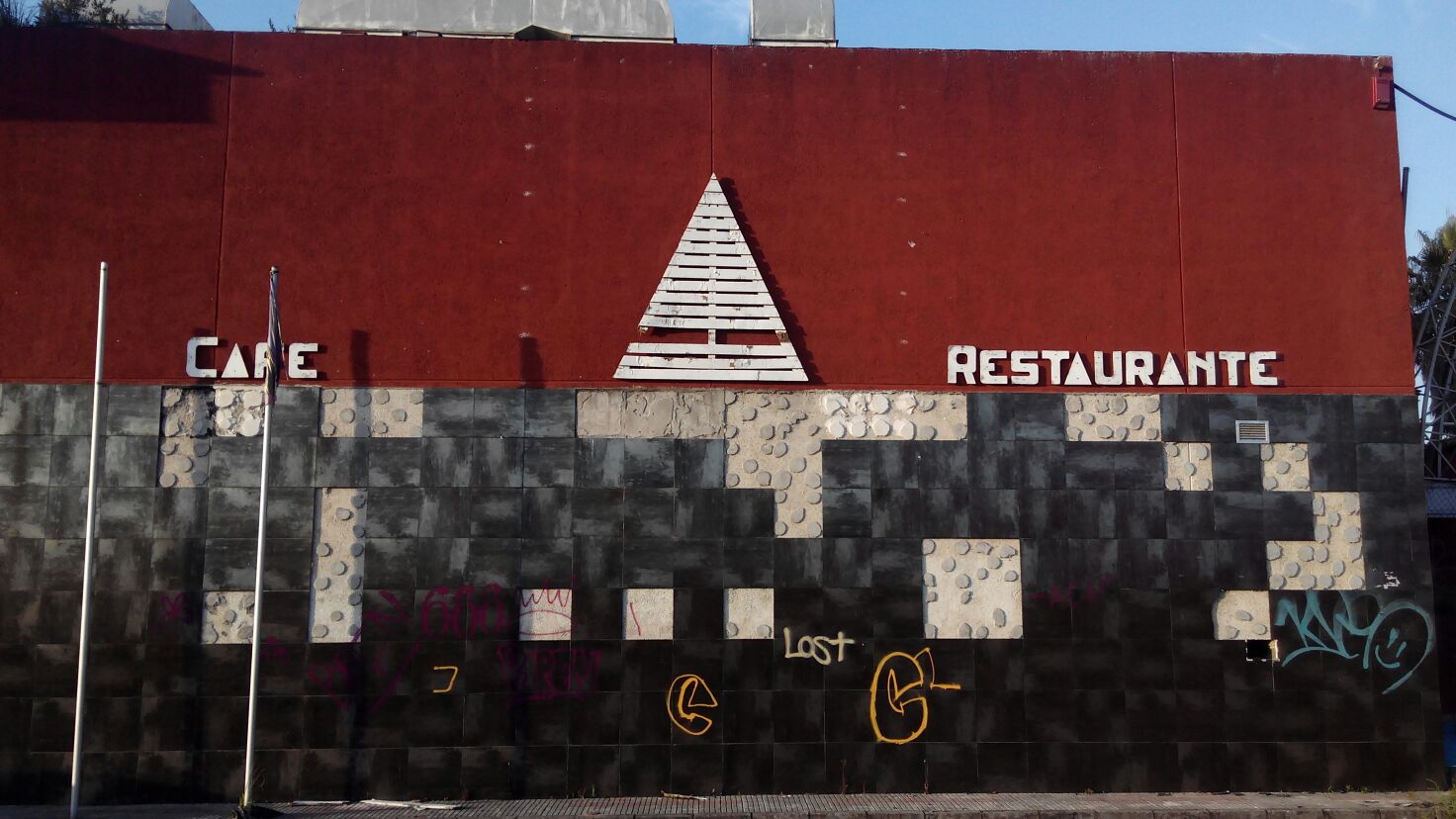
Discoteca Aqua
En 1989 cuando en Santander aún no existía ninguna gran infraestructura que acogiese eventos, en el Polígono de Raos (Camargo) se abrió una Macrodiscoteca llamada «Acqua«, un gran edificio orientado a eventos, conciertos y actos que tenía la última tecnología del momento y en sus más de 6.000 m podíamos ver una piscina o jardines. Desde Santander se ve su gran icono arquitectónico: la pirámide de Cristal. Tuvo su momento de gloria en los noventa, acogió la grabación de Gala Fin de Año de Televisión Española en 1993, la final de Miss España y cantantes de primera fila pisaron sus tablas.
Permanece abandonado, ahogado por las deudas y con un cambio de nombre, pasando por «Driza» hasta volver al «Aqua» hacia lo que puede ser, que esa pirámide que estamos acostumbrados a ver en el horizonte de la Bahía junto al Aeropuerto, desaparezca. Por suerte, aún permanece en pie sus neones y su peculiar tipografía geométrica de café / restaurante, donde las «A» son pirámides muy en la línea de su iconografía principal, realizada en madera.
Actualización: En verano de 2019 comenzó el proceso de su demolición lo que hizo que desapareciesen sus rótulos.
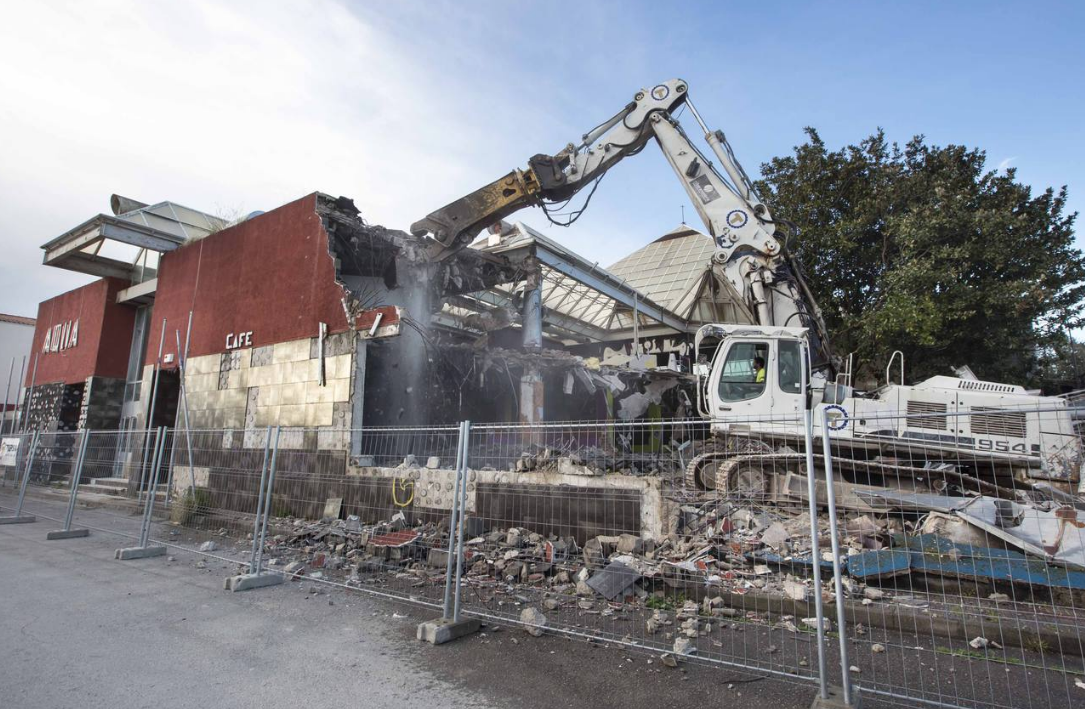
Imagen de la demolición de la Discoteca / Diario Montañés. Julio 2019.